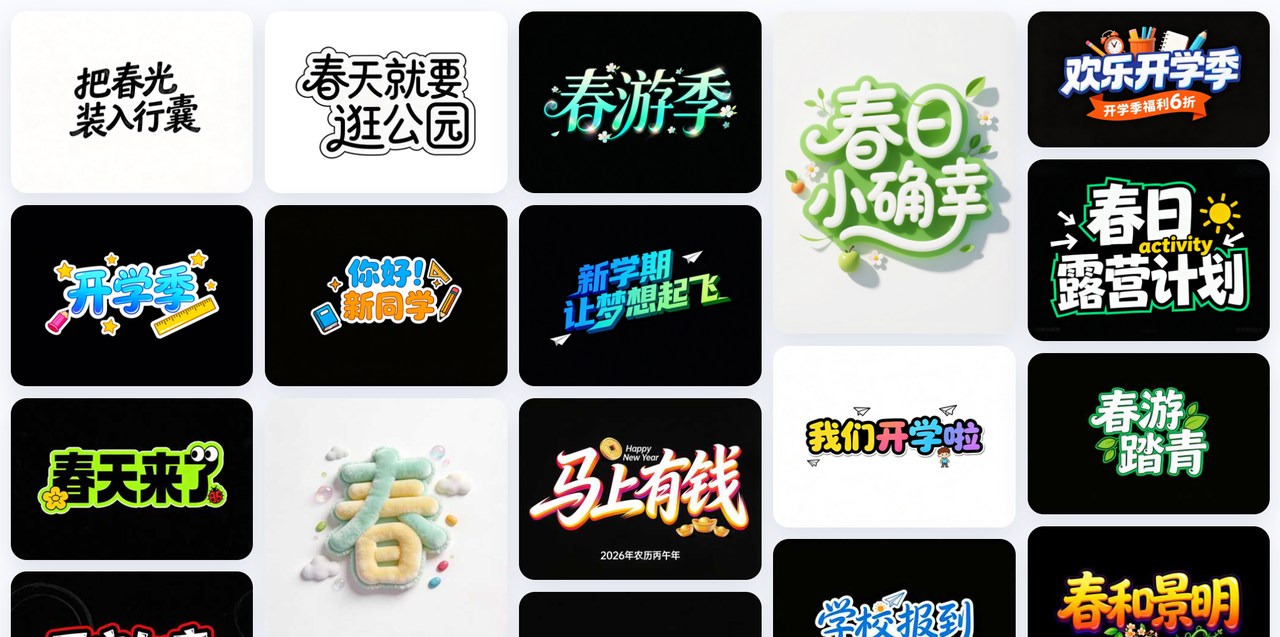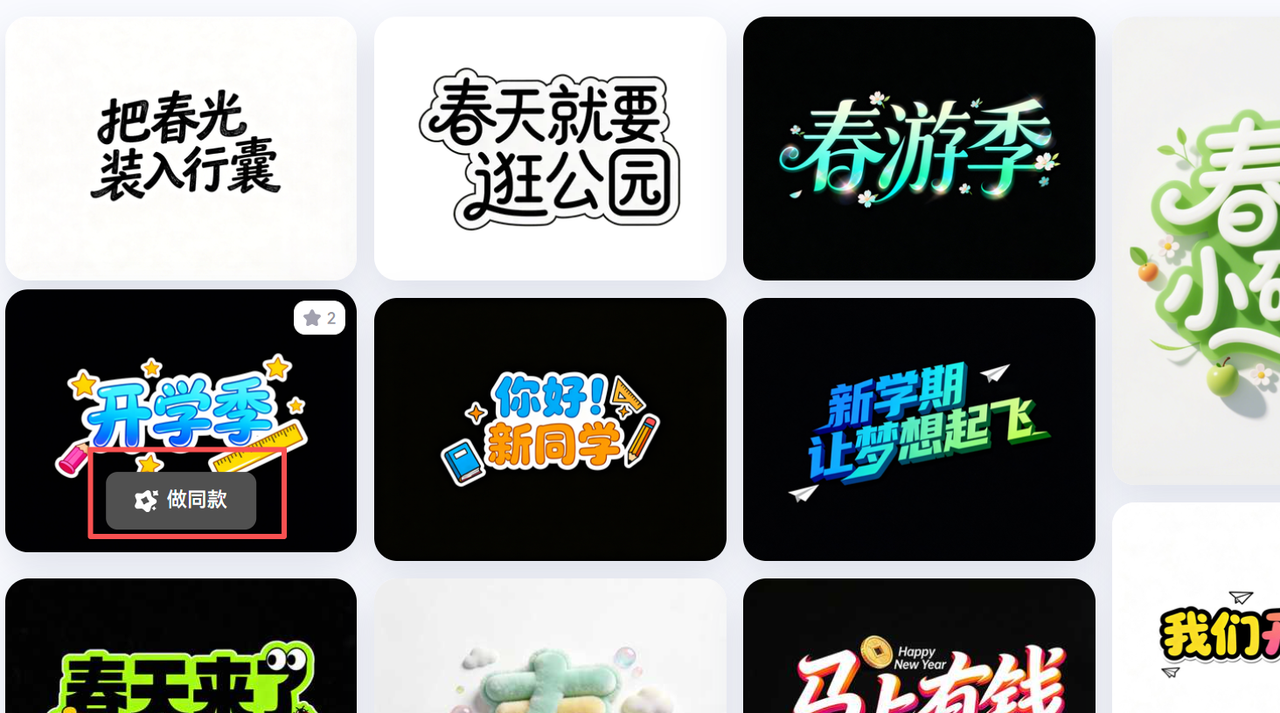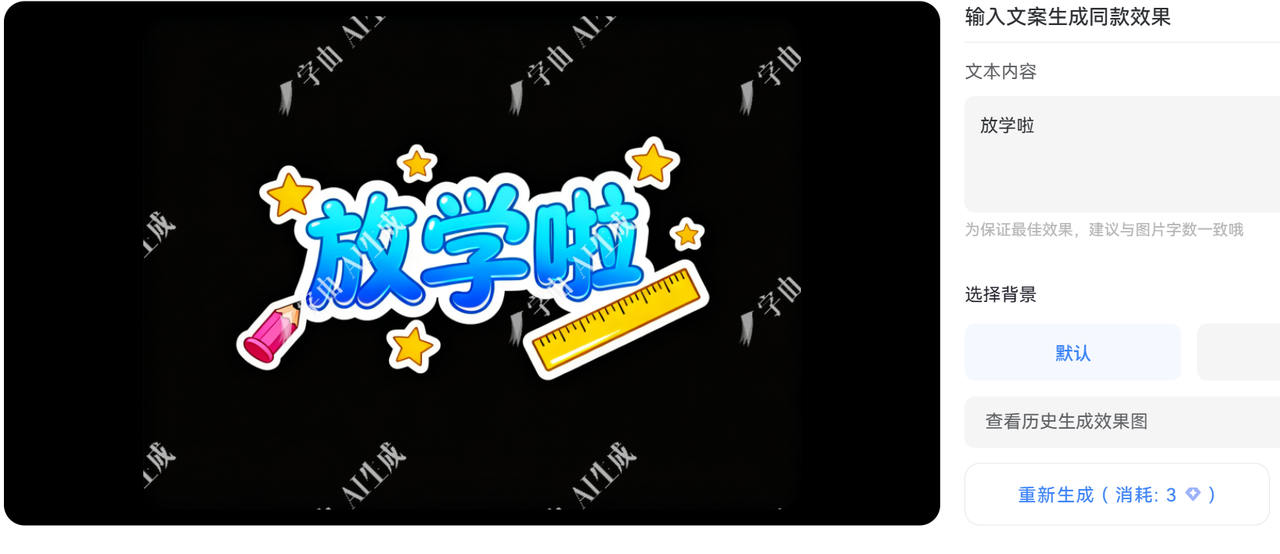
免费艺术字在线制作工具推荐,一分钟制作艺术字
当你设计一张充满个性的社交媒体配图,或者做一个吸引人的营销海报时,却发现普通的字体显得那么“普通”,渴望为你的文字赋予独特的风格,变得更加引人注目。今天,我就要把我私藏的几个免费艺术字在线制作工具分享出来,让你也能轻松的制作艺术字。
字由 AI 生成字体
字由推出的AI字体工具,非常适合新手和非专业设计师,只需找到符合你需求的艺术字模板,然后输入自己的文案,就能快速设计出自己的在线艺术字。
根据场景和风格选择自己想要生成的艺术字方向
点击“做同款”
找到自己喜欢的艺术字模板,点击"做同款"
输入自己的文案
输入自己的文案,点击生成,等待一会儿,就会生成相同效果的艺术字了
艺术字生成的独立工具
这类工具可能没有那么多的附加功能,但它们专注于“艺术字生成”这一件事,往往能提供更专业、更具风格化的艺术字效果。
- WordArt.com
这个网站曾经是很多人的“艺术字启蒙”。它提供了非常多种艺术字风格,包括各种纹理、形状、颜色搭配。你可以在这里输入文字,选择风格,调整颜色、形状,然后下载。它尤其擅长制作一些具有装饰性、复古感的艺术字。
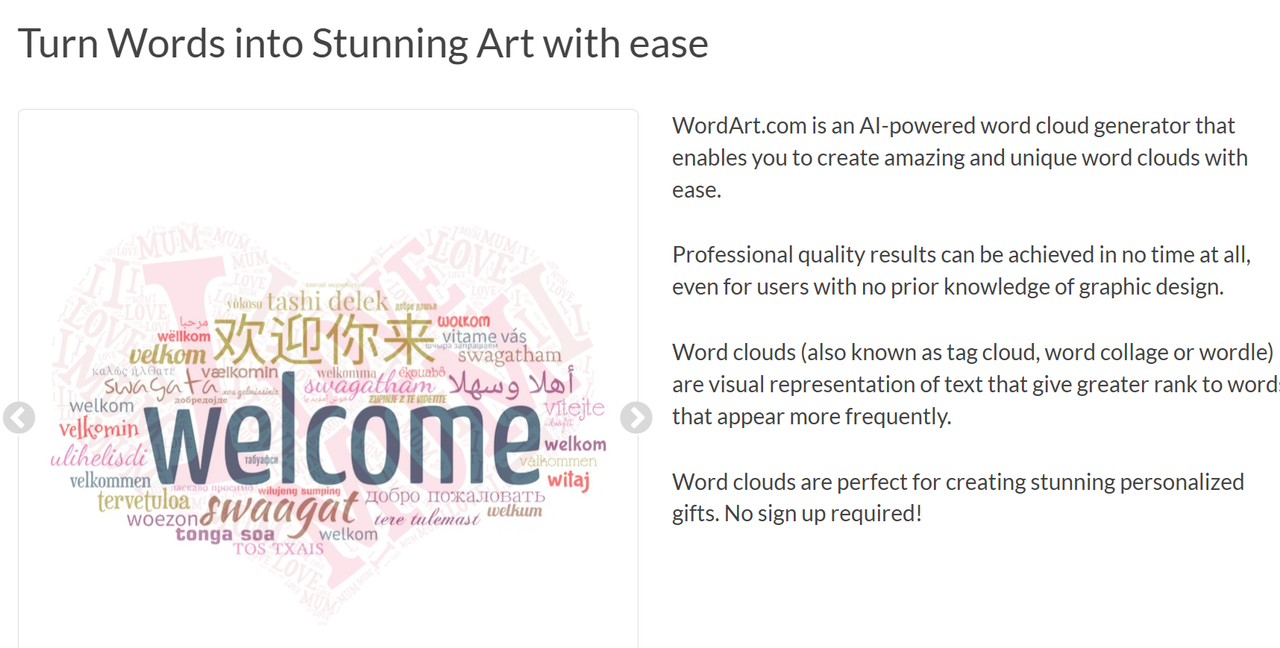
- CoolText.com
CoolText是另一个经典的艺术字生成网站。它提供了非常多样的艺术字模板,从简单的颜色渐变到复杂的3D效果、火焰、冰块等等,应有尽有。你可以在这里自由选择字体、大小、颜色、纹理,甚至添加Logo标志。操作也很直观,生成速度快。
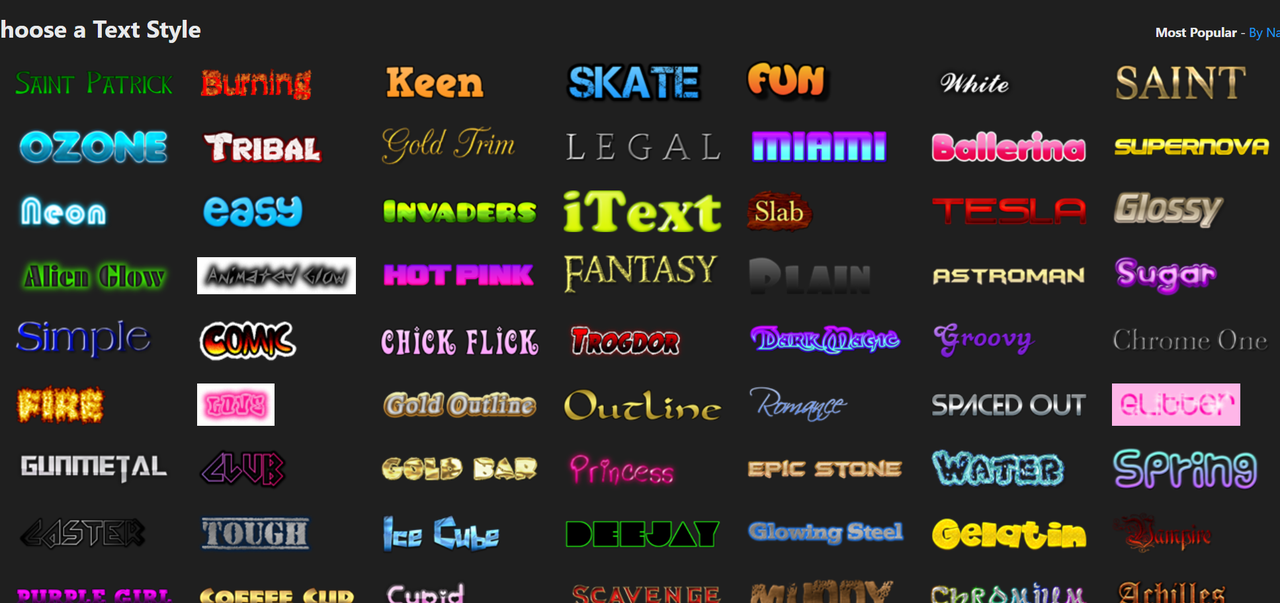
- Text Giraffe
这个网站专注于生成一些比较炫酷、特别是3D风格的艺术字。它提供了很多预设的3D模型和材质,你可以选择一个喜欢的模型,然后输入自己的文字进行替换,调整颜色和光照效果,就能生成非常具有视觉冲击力的3D艺术字。
综合型在线设计平台
这类平台通常不仅仅提供艺术字制作,还集成了海报、Logo、PPT模板等多种设计功能,让你可以在一个地方完成多种设计任务。
- Canva 可画
Canva 不仅有海量的精美设计模板,它的“文字”功能也非常强大。你可以直接添加文本框,然后在其“样式”或“效果”选项中找到各种艺术字效果,比如描边、阴影、倾斜、背景、霓虹灯效果等等。它还内置了非常多好看的字体,并且允许上传自定义字体。
- 稿定设计
稿定设计是中国本土一个非常优秀的设计平台,它的艺术字制作功能也很强大。你可以在“素材”中心搜索“艺术字”或“艺术字生成器”,会找到很多专门的艺术字模板和工具。它提供了很多具有中国风、节日特色、或者潮流感的艺术字样式,你可以直接替换文字,调整颜色,非常方便。
- Fotor懒设计
Fotor也提供了类似Canva和稿定设计的在线设计服务。它的艺术字制作功能也很不错,同样支持丰富的文字效果和模板。你可以在它的“素材库”中找到各种艺术字样式,然后进行编辑。